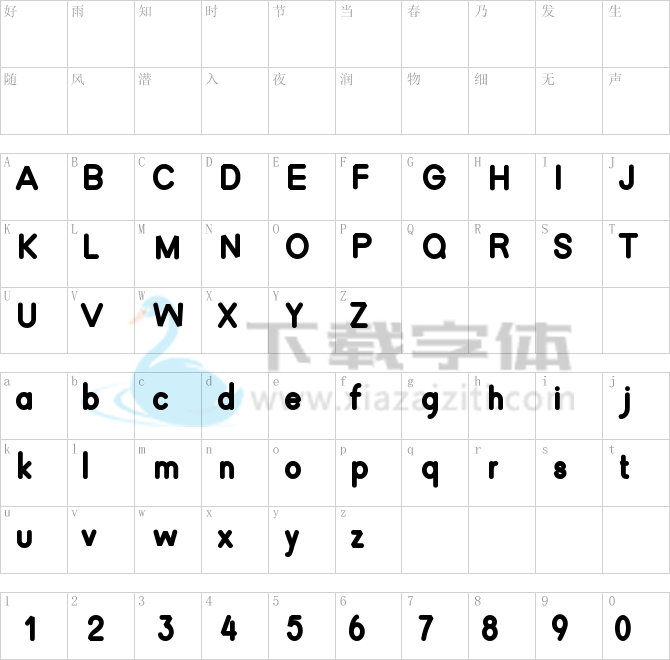
Affection.ttf字体下载,这款字体结构工整、笔画清晰,兼顾美观与易读性,适用于标题、正文、海报、包装、LOGO 等多种场景。字形优雅稳定,风格百搭耐看,适配日常排版与创意设计,让文字呈现更舒适、更具质感。Affection.ttf字体下载一笔一画,皆是细节,以均衡的比例、流畅的线条打造舒适视觉体验,字形端正大气,风格简约现代。无论是商业设计、品牌宣传还是日常排版,都能轻松驾驭,让文字更有格调与力量。Affection.ttf字体下载字体下载。